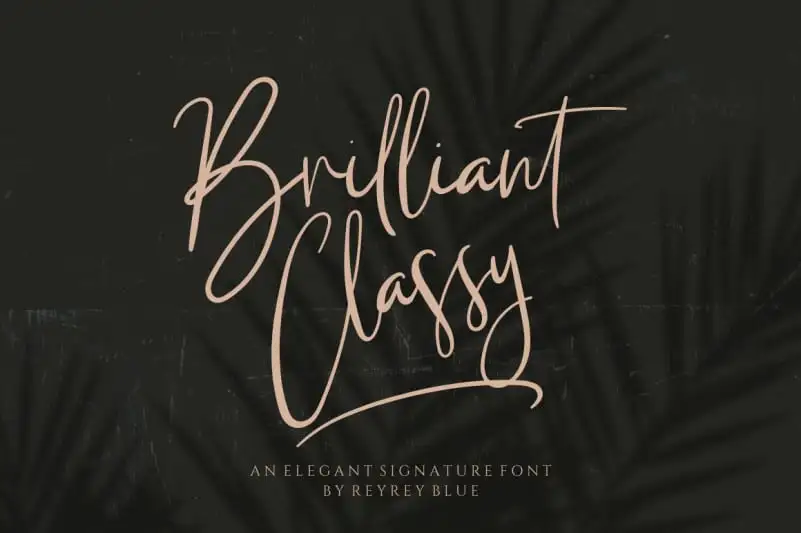
Brilliant Classy Script Font – Download Grátis
Introduzimos a Brilliant Classy Script Font, uma elegante fonte tipográfica que combina modernidade com feminilidade. Este é um tipo especializado para designers gráficos que buscam um estilo sofisticado e profissional para seus projetos de marca ou logomarca. Além disso, também é perfeito para aplicativos como design editorial, cartões de convite, mensagens personalizadas e outros trabalhos que exigem uma escrita a mão realista. A Brilliant Classy oferece um conjunto completo de letras maiúsculas e minúsculas, números e uma grande variedade de pontuação, incluindo 91 ligaturas perfeitas para criar aparências ainda mais naturais e profissionais. Esta fonte é ideal para quem deseja dar um toque único a seus projetos digitais ou físicos. Se você procura por uma fonte que combine modernidade com elegância sem abrir mão de detalhes finos, não tem dúvida que a Brilliant Classy Script Font é o tipo perfeito para atendê-lo.